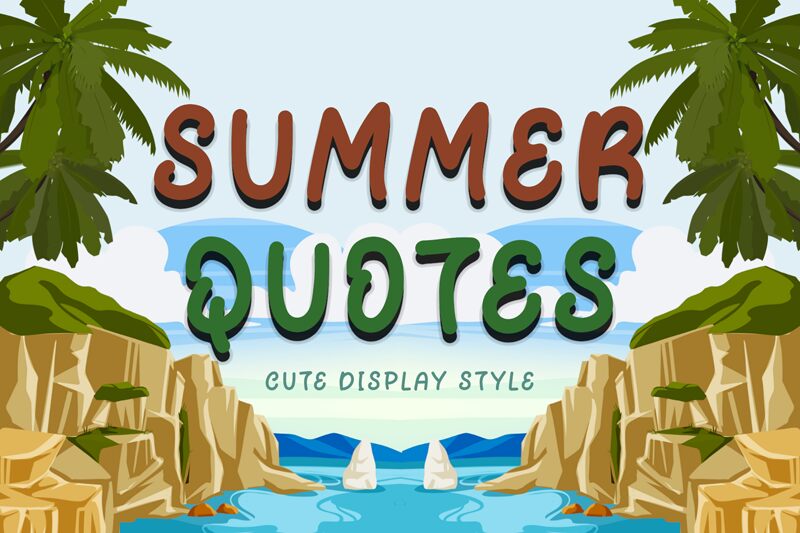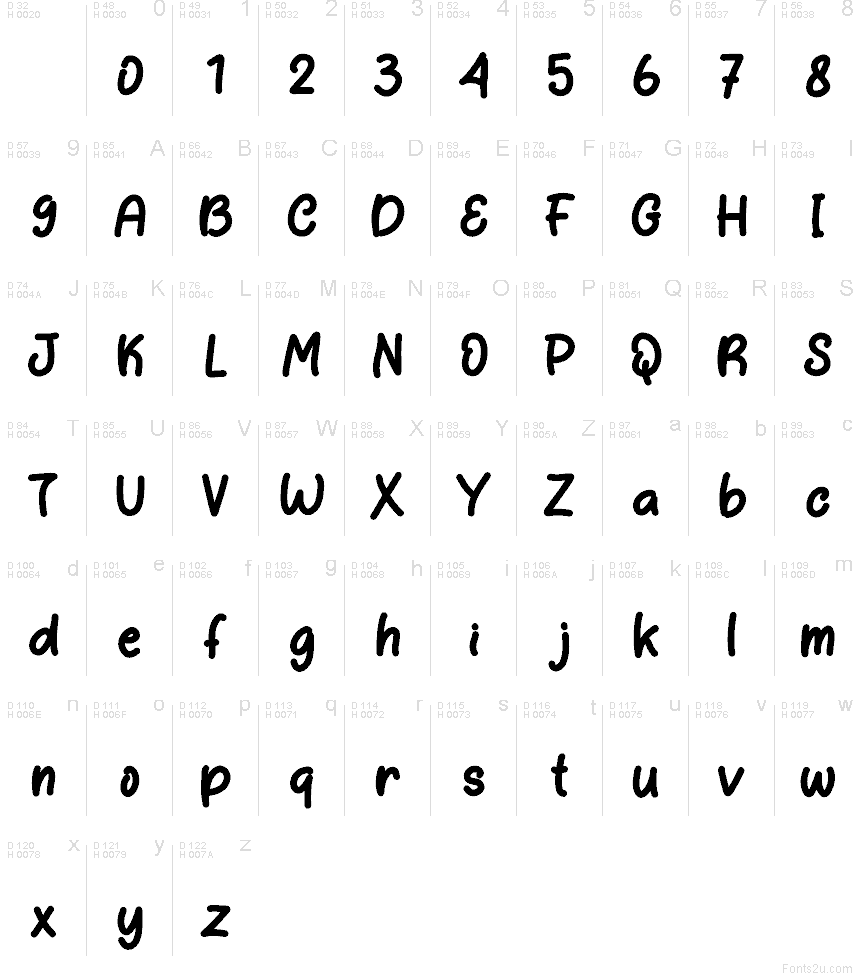
Summer Quotes Demo
Summer Quotes é uma fonte manuscrita gratuita com traços fluidos e curvas suaves e descontraídas. As letras mantêm um ritmo constante, com um estilo manual relaxado que parece informal, mas nunca desleixado.
Summer Quotes é ideal para imagens com citações, cartões de felicitações, posts em redes sociais, cabeçalhos de blog e convites curtos onde um toque pessoal faz toda a diferença. Esta fonte gratuita também se adapta bem a etiquetas de embalagens, detalhes de logotipos e branding de estilo de vida, pois suas formas ligadas conferem a frases curtas um acabamento artesanal autêntico.